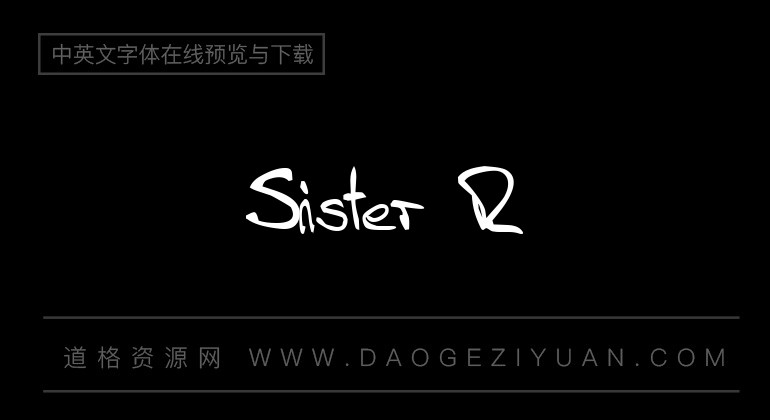
Sister R
Sister R 是一款由英国设计师Rob Clarke设计的手写字体。它是一种模仿手写体的字体,有着温暖的感觉,可以让你的设计更加有趣,更加有趣。它具有轻盈的线条,可以用来制作漂亮的标题,也可以用来制作精致的文字效果。它的设计灵感来自Rob Clarke的妹妹,所以取名为Sister R。
Sister R是一款非常不错的手写艺术字体,具有很好的视觉感,适合于文化类的宣传设计、商业类品牌的广告和产品包装设计以及个性化文字排版等较多场景。